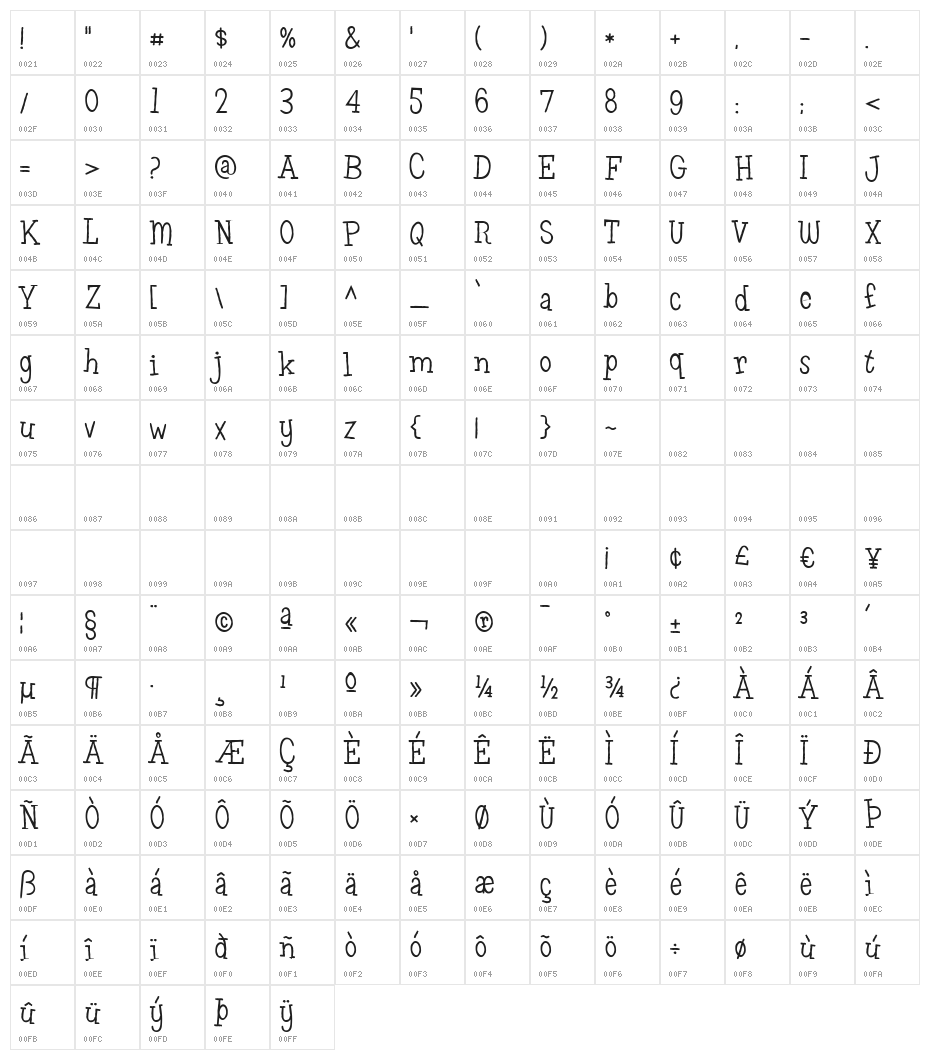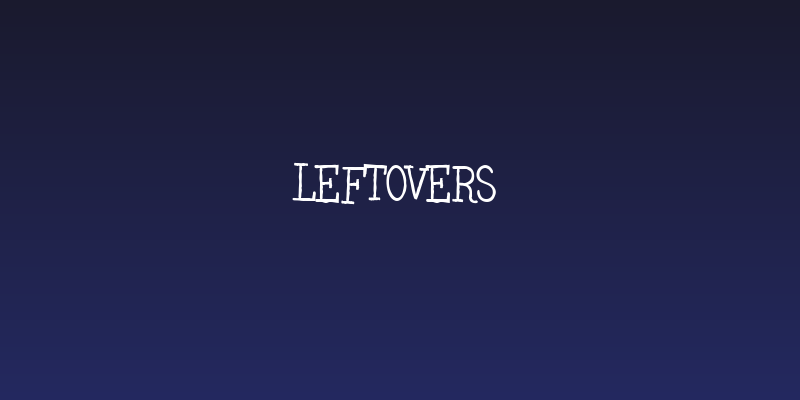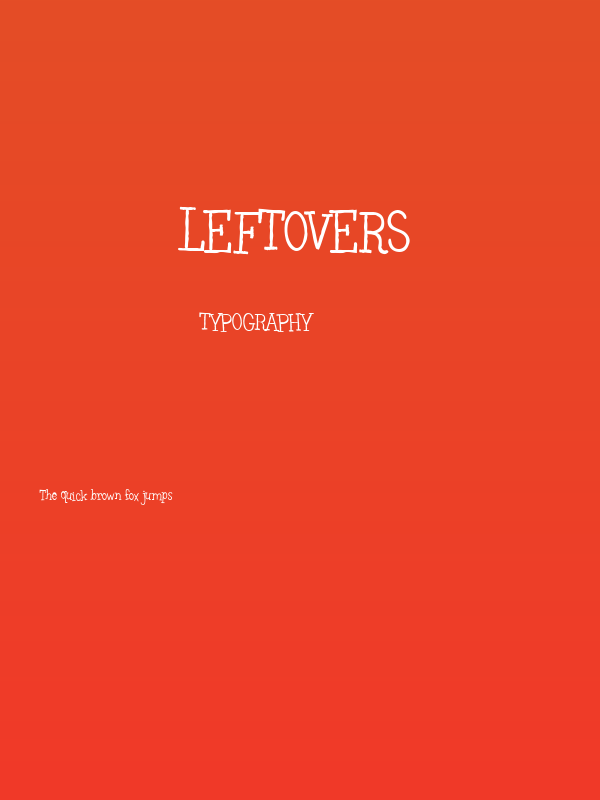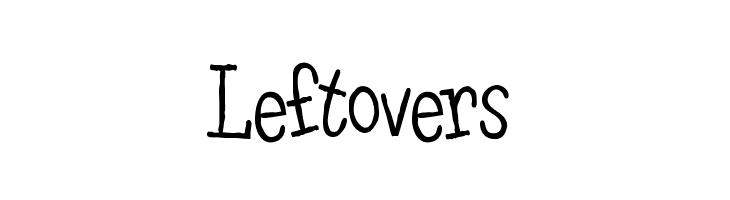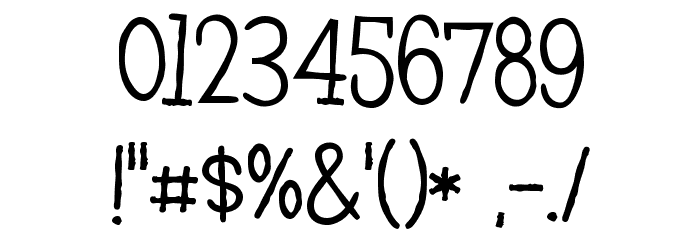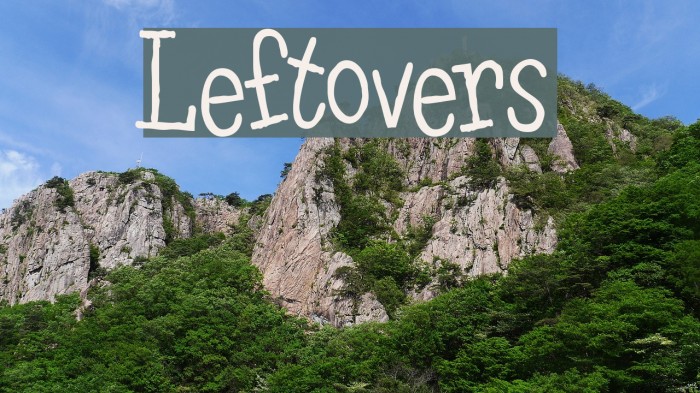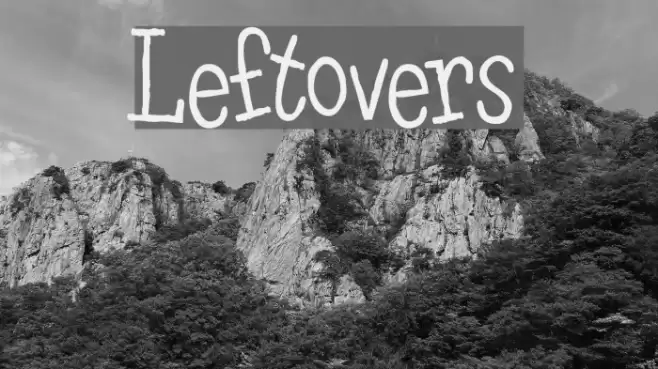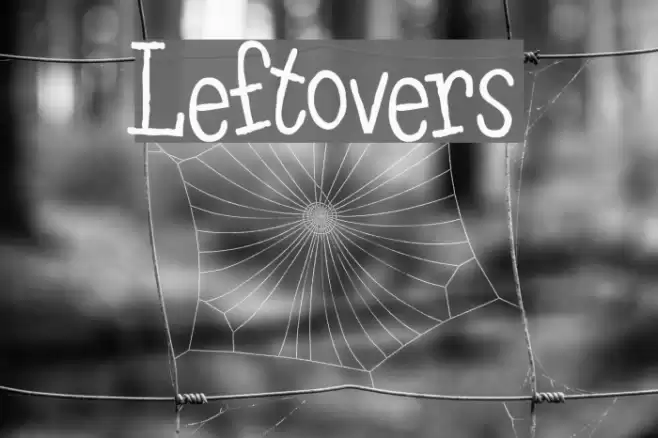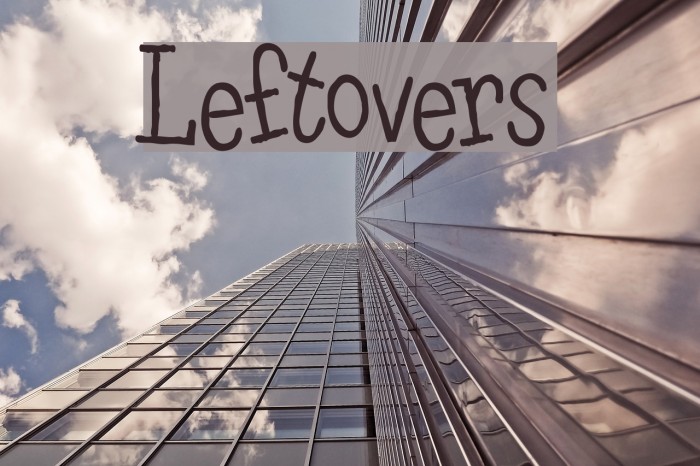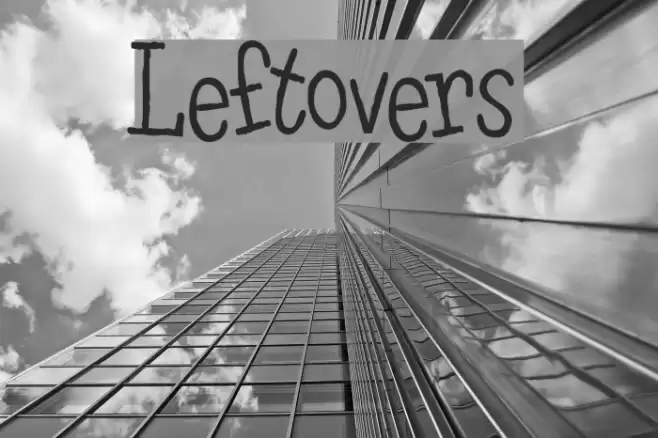
Leftovers Font
| Caso d'uso | Headlines, Logos, Informal Text |
| Progetti proposti | Ideal for children's books, greeting cards, playful branding, and casual invitations. |